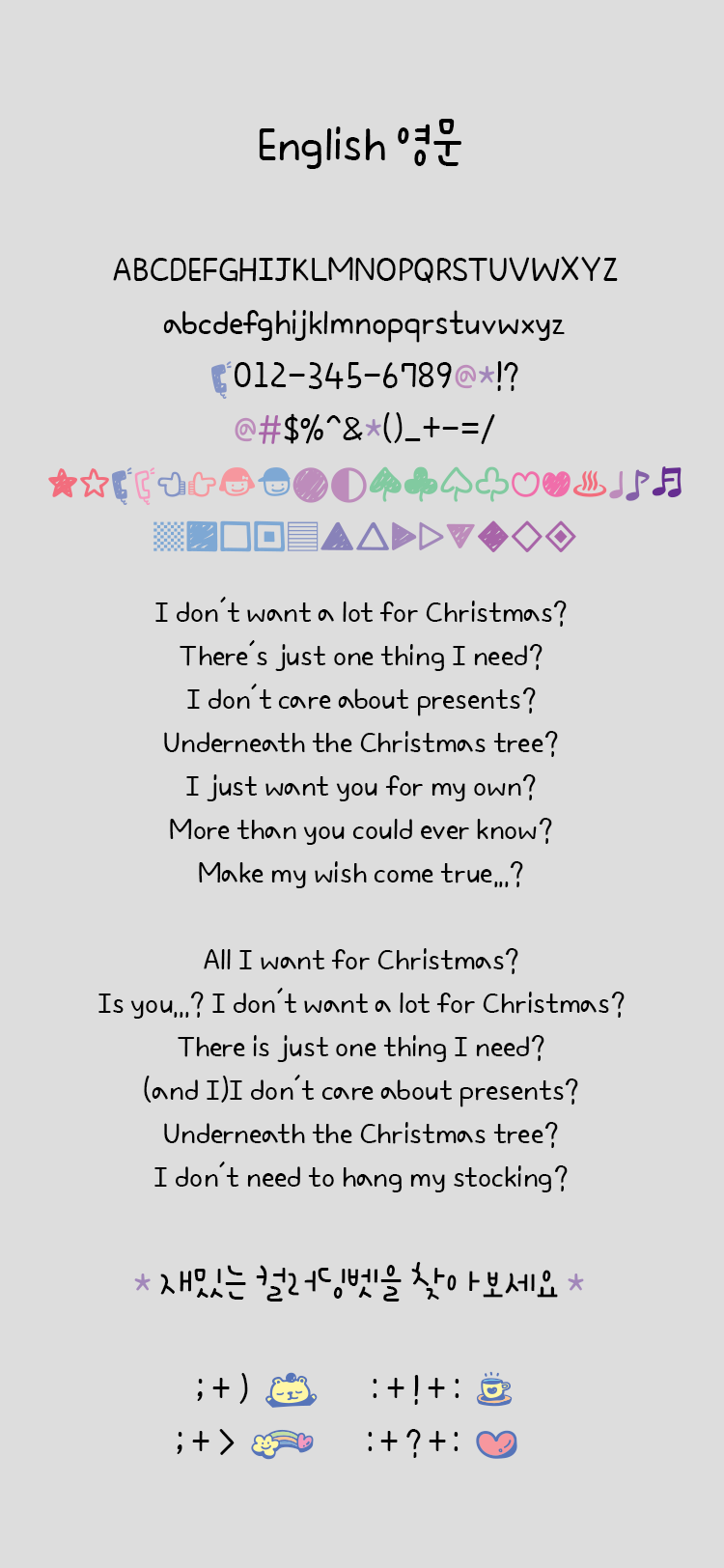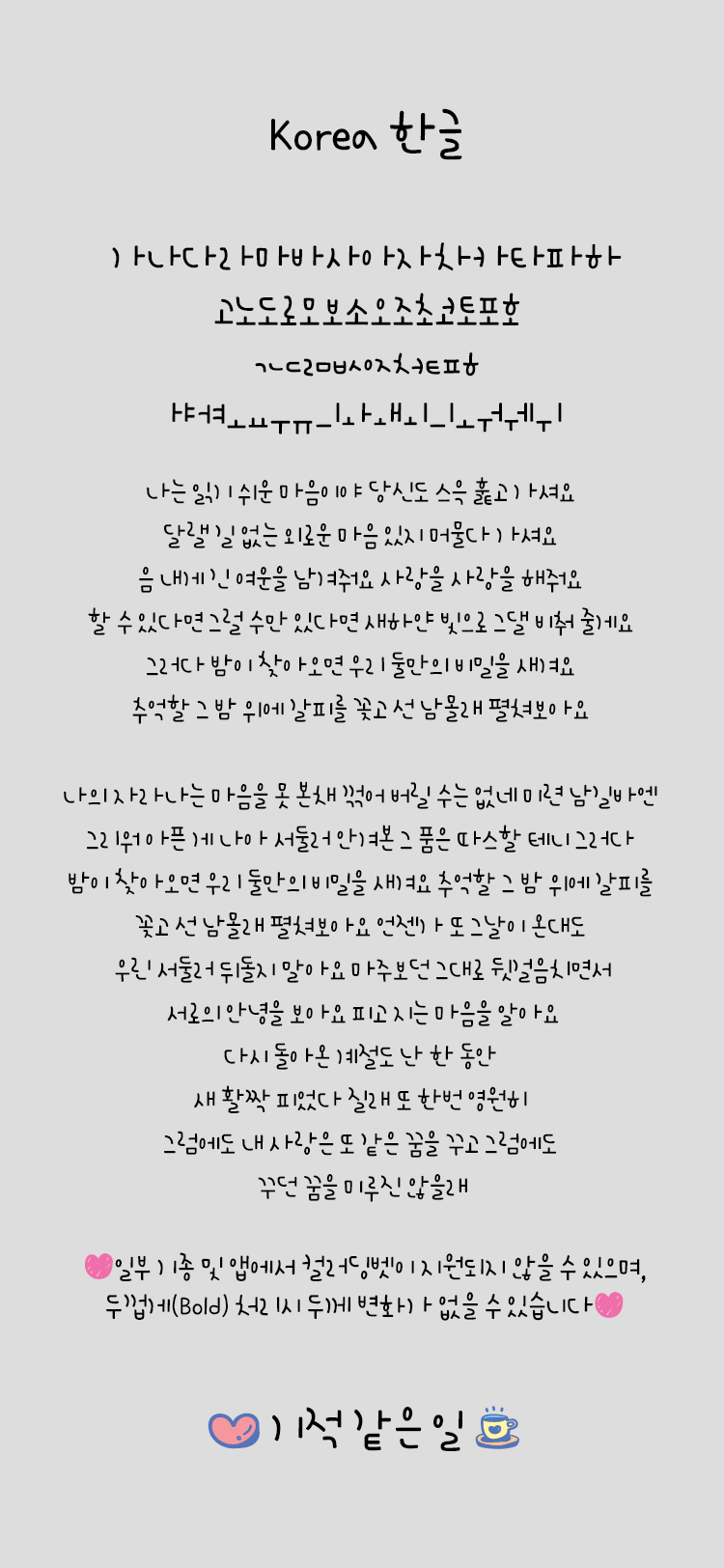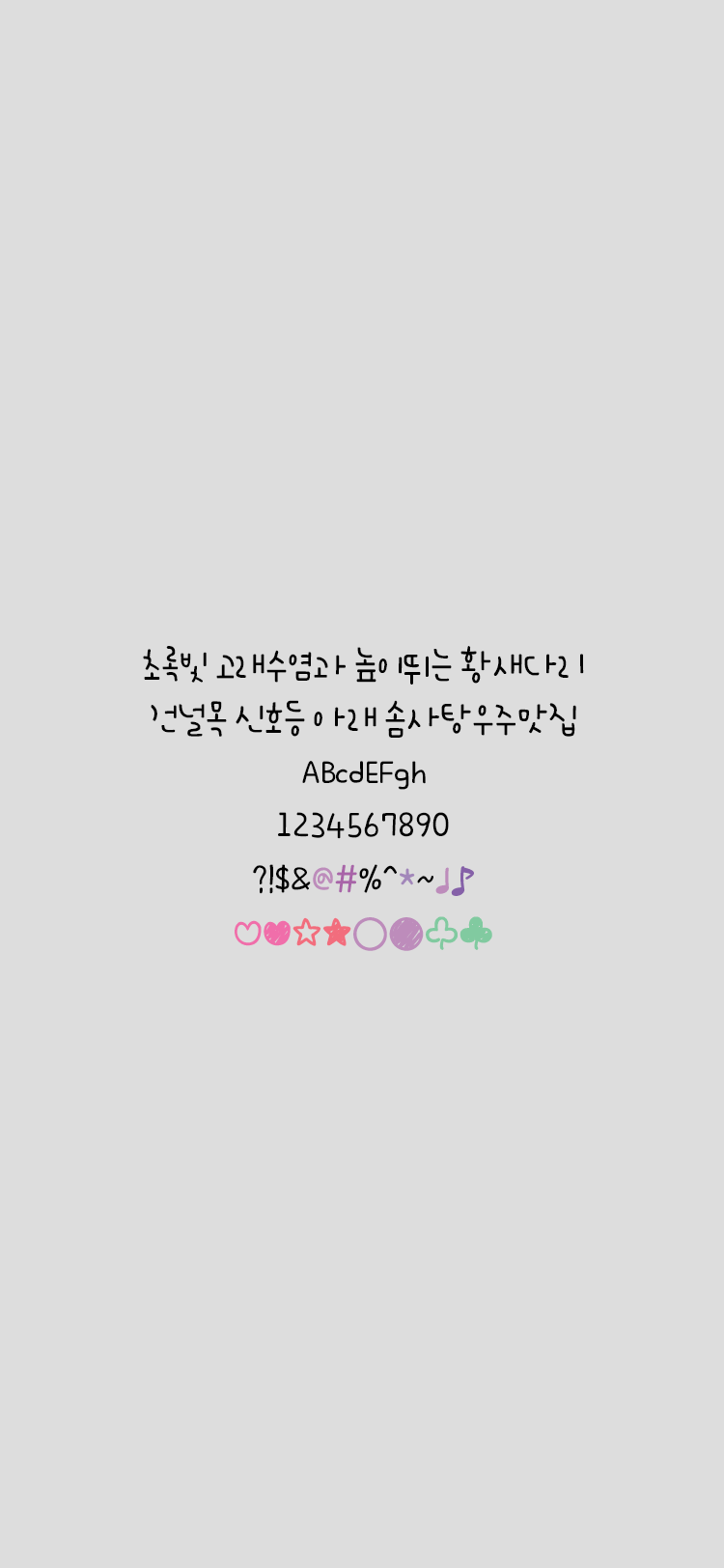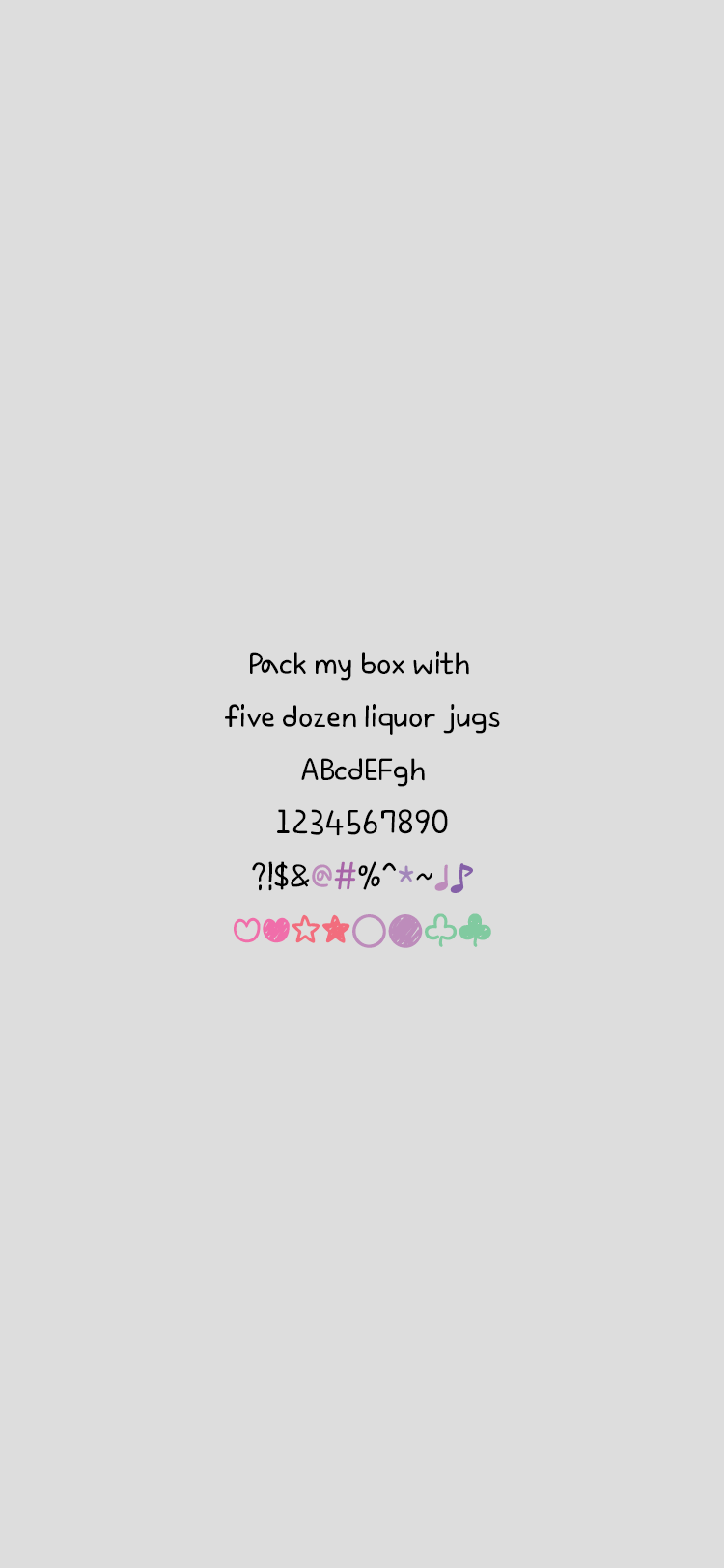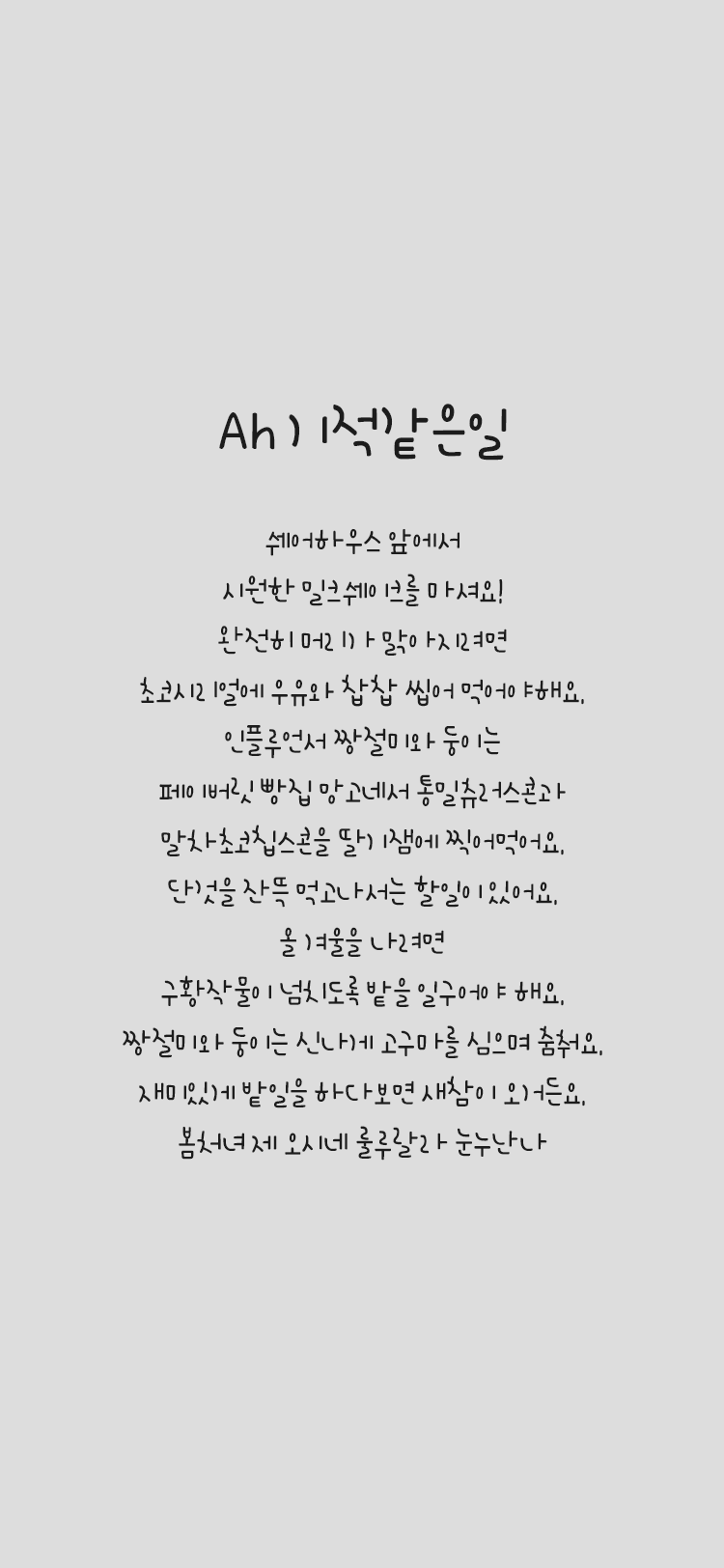
Ah 기적같은일
이 서체는 자소들을 손으로 또박또박 쓴듯하면서도 자연스러운 형태가 특징입니다.
글줄은 중하단으로 시각적 흐름으로 설정하여 가독성 또한 장문으로 사용 시에도
무리 없도록 제작 하였습니다.
특별한 히든딩벳이 숨어져 있으니 찾아보시기 바랍니다. :>
• 손글씨
• Ah 기적같은일 / Ah Miracle